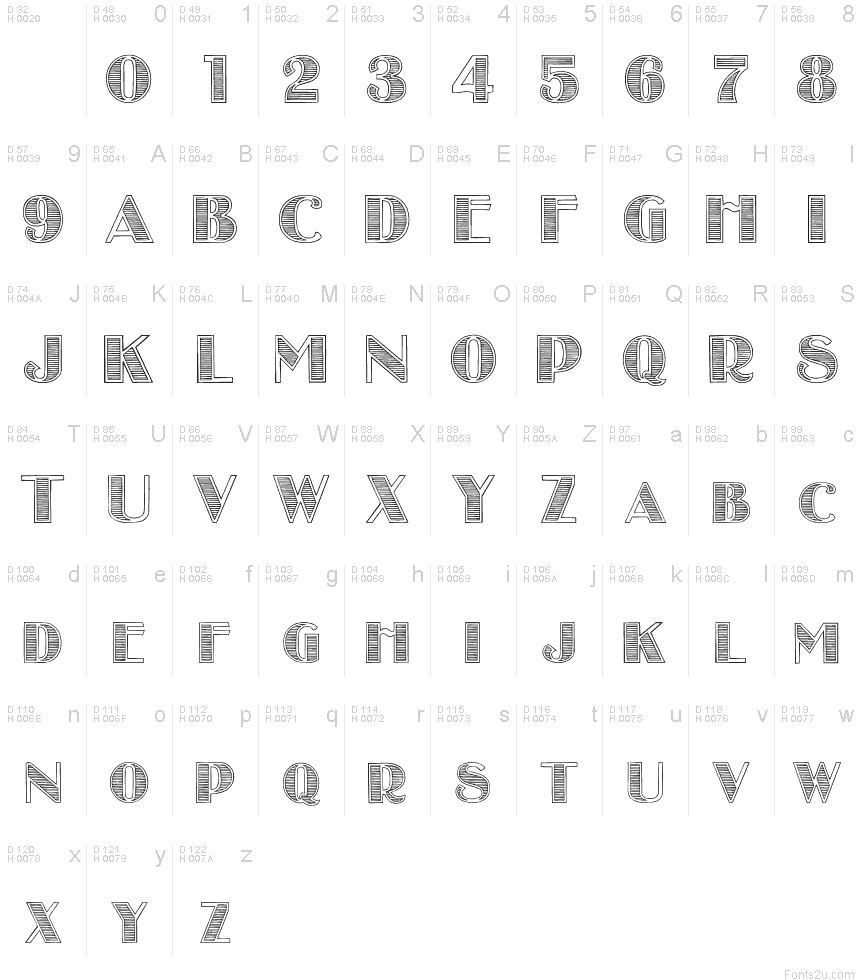
Stripes Caps to darmowy, pasiakowy font typu display od Lime 2000, utrzymany w klimacie plakatów vintage. Szerokie litery wypełniają wąskie poziome pasy, zamknięte w czyste zewnętrzne kontury. Krój jest lekki, a zarazem wyrazisty, łącząc klasyczne proporcje z lekko ornamentalnym rytmem, który nadaje mu graficznego sznytu bez efektu przekombinowania.
Świetnie sprawdza się na szyldach retro, nagłówkach w magazynach, opakowaniach, tytułach i monogramach, gdzie pasiakowa tekstura sama w sobie stanowi ozdobę. Jako darmowy font najlepiej prezentuje się w krótkich napisach – szczególnie wtedy, gdy chcesz uzyskać efekt odręcznego liternictwa, a nie zwykłych blokowych znaków.